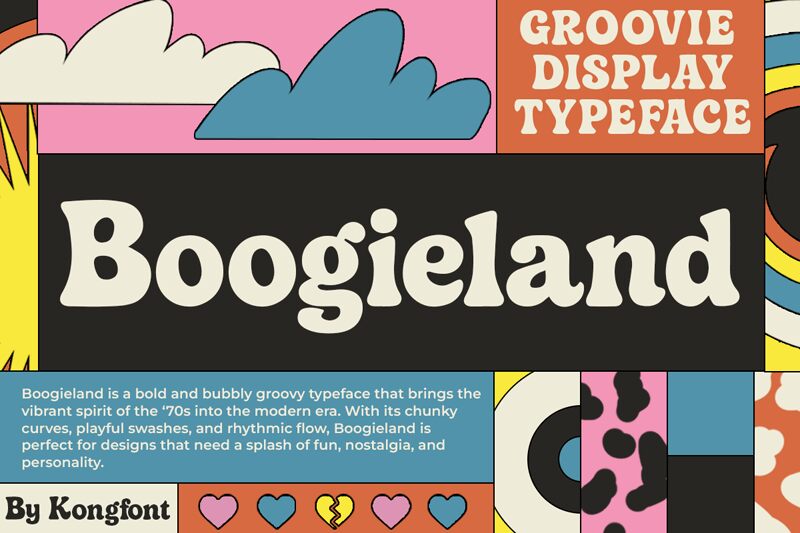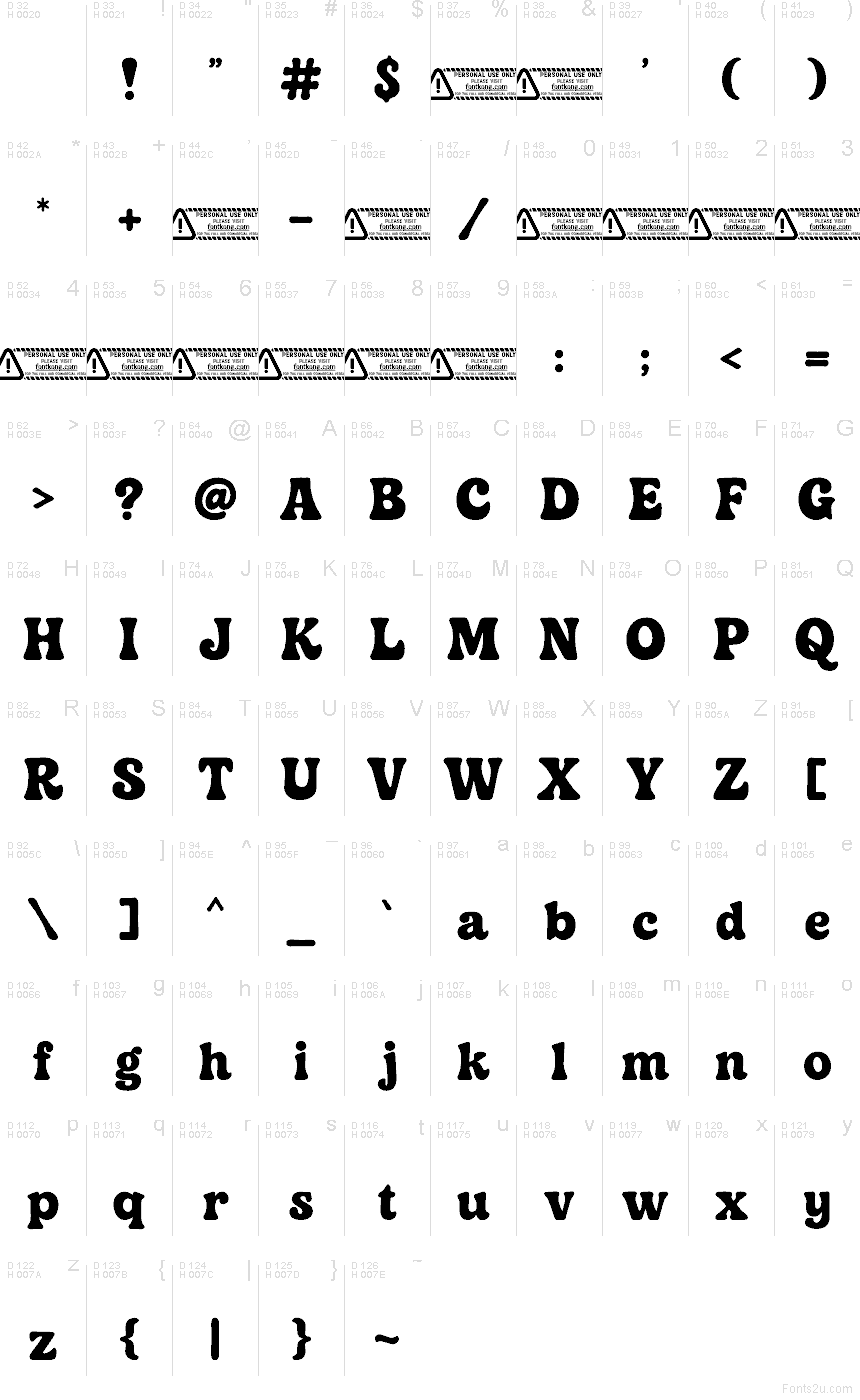
Boogieland من Kong Font هو خط عرض (Display) مجاني بأسلوب Groovy، يتميز بصورة ظلية مستديرة وممتلئة تذكرنا فوراً بخطوط ملصقات السبعينيات. تضفي المنحنيات العريضة، والوصلات الضيقة، والتوازن المتذبذب قليلاً على التصميم مرونة انسيابية، مما يجعل الخط يبدو وكأنه نتاج حركة طبيعية وليس مجرد هندسة صارمة.
تعتبر هذه الخامة مثالية لمنشورات الحفلات الموسيقية، والعلامات التجارية للمقاهي ذات الطراز القديم، وأغلفة الألبومات، ودعوات الحفلات، وعناوين التواصل الاجتماعي الكبيرة، حيث تعمل الحروف كأشكال رسومية بقدر ما تعمل كنصوص. تستفيد العناوين القصيرة بشكل خاص من إيقاع الخط العضوي، مما يضفي لمسة ديسكو مريحة دون الحاجة إلى زخارف إضافية.